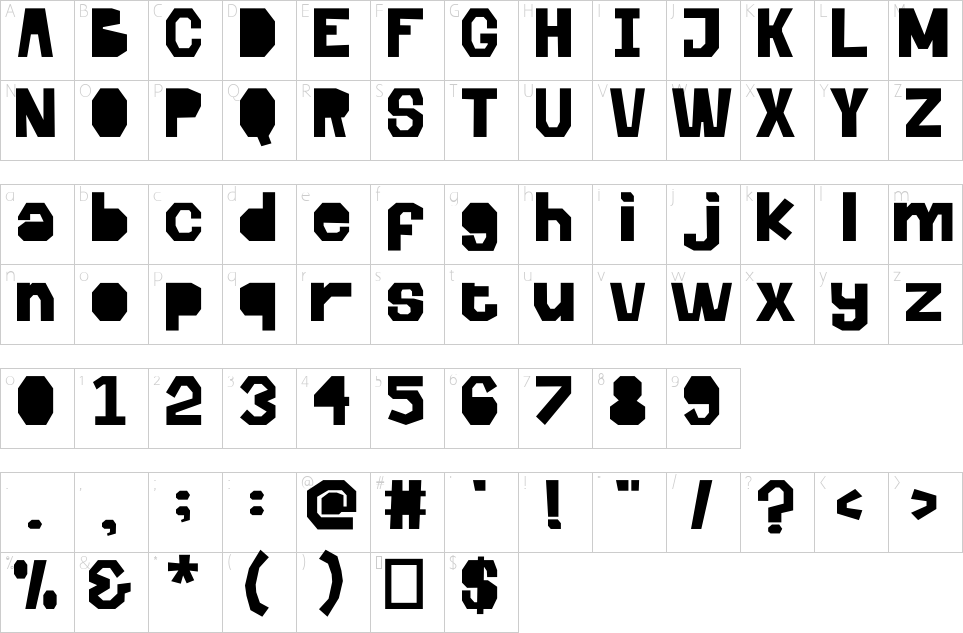
A fonte Paperott é uma escolha perfeita para quem está em busca de uma fonte de papel com uma aparência encantadora e natural. Desenvolvida por Jada Akbal, esta fonte oferece um charme que transmite uma sensação de liberdade e naturalidade, tornando-a perfeita para projetos de texto agradável aos olhos e para projetos de design gráfico. Com seu design cuidadosamente pensado, Paperott é perfeito para estilos de design que valorizam a simplicidade e a elegância, adaptando-se perfeitamente para criações digitais que buscam uma aparência autêntica e sofisticada. É uma fonte que reflete a essência do mundo de hoje, onde o conforto e a simplicidade ainda são valorizados, e está disponível gratuitamente para download tanto no Windows quanto no Mac, facilitando para qualquer um que deseja incorporar um toque autêntico e agradável em seus projetos digitais.